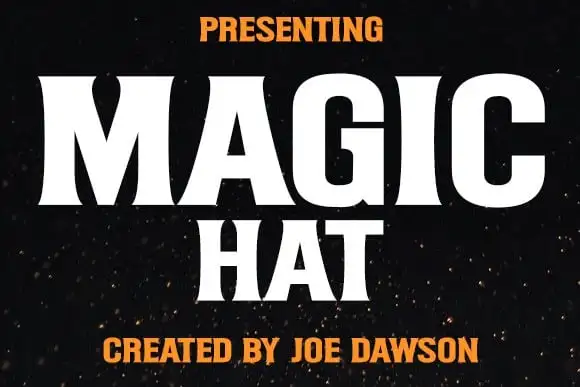
Magic Hat Display Font – Download Grátis
Magic Hat Display Font é uma tipografia poderosa e bold, projetada pelo designer Joe Dawson, especialmente concebida para destacar seus ideais criativos. Seu traço grosso e robusto transforma qualquer texto em um texto de página de capa marcante, adaptável a diversas aplicações de design como rótulos de livros, cartazes de filmes, identidades de marca e bandeiras comerciais. O seu poderoso estilo é perfeito para comunicar mensagens com força e autoridade, tornando sua mensagem ainda mais impressionante e memorável. Seja você um criador digital ou designer gráfico, o Magic Hat Display Font será a escolha certa para criar um impacto visual notável em seus projetos.